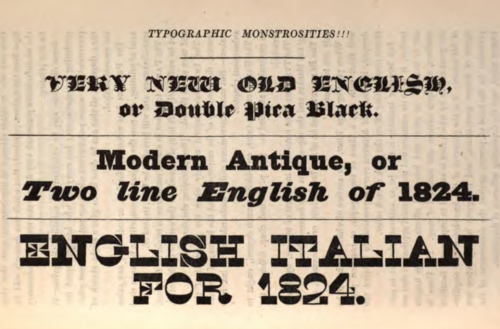
逆コントラストまたは逆ストレスの書体とは、ストレスが標準と逆になっている書体またはカスタムレタリングであり、つまり横線が最も太い。これは、縦線が横線と同じ幅か横線より太いというラテンアルファベットの書き方、特に印刷では普通のことであるが、その逆である。[5] [6] [7] [8] [9]その結果、文字が逆向きに印刷されているように見えるという劇的な効果が得られる。このスタイルは、19世紀初頭にディスプレイ書体の目を引く目新しいものとして発明された。このジャンルのデザインを作成した現代のフォントデザイナー、ピーター・ビラクは、これを「目立つ奇妙な書体を作成するための卑劣なトリック」と表現している。[10]
逆コントラスト文字は本文にはほとんど使われず、見出しやポスターなどの表示用途で使われることが多く、その珍しい構造は特に目を引くことがある。 [11] [12] 19世紀に特に一般的で、それ以降も時折復活している。太いセリフのためスラブセリフデザインとみなされ、そのジャンルの一部として特徴付けられることが多い。[7] [13]
逆コントラスト効果は、サンセリフ体などの他の種類の書体にも拡張されています。[7] [14]明るい文字が黒い背景に印刷される逆コントラスト印刷とは関係がありません。 [15]
歴史的背景
大文字はローマ字の角張った大文字、小文字は手書き文字をベースにした現代ラテン文字の発展を通じて、縦線は横線よりわずかに太いのが一般的だった。初期の「ローマン」または「アンティクア」書体はこのモデルに従い、文字の最も細い部分を斜めにし、下線を上線より太くして、右利きの筆者が羽ペンで書いたような書き方を模倣していた。(対照的に、ヘブライ文字はラテン文字の観点から見ると通常「逆コントラスト」で、縦線が薄くなっている。[16])
1475年頃にローマン体が登場してから18世紀後半にかけて、文字のデザインは比較的あまり発展しませんでした。当時のフォントのほとんどが本文用であり、デザインも比較的似通ったままで、イタリアの人文主義的な手書きの伝統に根ざしていたからです。[b]
17 世紀以降、活字鋳造工は現在では過渡期型、そして「モダン」またはディドン型と呼ばれる書体を開発しました。これらの書体は、以前よりもはるかに大きなストロークのコントラストを持ち、ストロークの幅の差も以前の書体よりもはるかに大きくなっていました。[d] [18] [19] [20]これらの書体は、当時の鋼鉄のようなカリグラフィに追いつくように、より構造化された文字形状を持ち、大胆に細い横線とセリフのディテールは、当時のますます高品質になる紙と印刷技術を誇示するものでした。[21] [22]さらに、これらの書体は厳密に垂直方向に強調されていました。例外なく、垂直線は水平線よりも太く、より幾何学的でモジュール化されたデザインを生み出しました。
この時期の2つ目の大きな発展は、印刷されたポスターの登場と、宣伝や広告のための看板や印刷物の使用の増加でした。これにより、目を引く新しいタイプの文字を開発したいという欲求が生まれました。[23]その結果、太字の「ファットフェイス」、古代に触発されたと思われるサンセリフ文字、そしてスラブセリフなどの新しいスタイルのレタリングと「ディスプレイタイプ」が登場し始めました。[24] [3] [25]これらの文字形態は、従来のセリフ文字の単なる拡大版ではなく、新しい出発点でした。[26] [27]おそらくより目を引くように、これらの新しいスタイルの文字は、非常に太字になることが多かったです。[2]
最初の逆コントラストタイプ
最も古い逆コントラストの書体は、1821年頃にさかのぼります。これはロンドンのキャスロン書体鋳造所(当時はキャスロン・アンド・キャザーウッドと呼ばれていました)によって作成されました。おそらく、当時の鮮明で高コントラストの「ディドン」書体とレタリングを模倣したものと思われます。[5] [10] [28] [29] [30]大文字のみのデザインで、鋳造所の鋼鉄製マスターパンチは、ロンドンのセントブライド図書館のコレクションに残っています。[5] [e]
Caslon Italian 書体は、デザイン上明らかに「概念的」であり、太字の特徴を意図的に取り入れ、一つずつ反転させている。Nick Sherman は、「太字は細字になり、細字は太字になるという、線の太さを反転させる非常に文字通りのアプローチを示している」とコメントしている。[12] [31]この書体はセリフが非常に太いため、文字を構成するセリフとメインのストロークの間の隙間が非常に小さく、これは「E」や「S」などの文字に見られる。この効果をさらに衝撃的なものにするために、三角形のセリフが反転され (文字に接するにつれて細くなり、太くなることはない)、「A」の太い線が通常の右側の位置 (右利きの書き手の手書きに一致する自然な位置) から左側に移動され、文字が逆向きに描かれたように見える。ポール・ショーはプリント誌に寄稿し、これを「19世紀で最も奇妙なスラブセリフ書体の一つ」と評した。[13] [f]ポール・バーンズとクリスチャン・シュワルツはこれを「ひねくれた[が]確信と自信を持って行われた」と評した。[5]
キャスロン社は、この書体を「イタリア風」と呼んだ。当時、いくつかのディスプレイ書体はエキゾチックな名前を付けられていた。同時期に、サンセリフ(後にスラブセリフ)書体に「エジプト風」、スラブセリフに「アンティーク」という名前が付けられた。これは、より奇抜なディスプレイ書体が作られるようになった世紀後半にますます一般的になった。[26] [33]シールズは、「キャスロンとキャサウッドの書体より前の例の証拠は見つかっていない」と書いている。[7] ニコレット・グレイは、それが「おそらく」イタリア起源であると信じるつもりだったが、印刷に関するフランスの著述家フランシス・ティボードーの影響を受けていた。ティボードーは、1921年の著書「印刷の手紙」で、このスタイルはフランス第一帝政(1804年 - 1814年/15年)の間にフランスで登場し、その後イギリスで初めて登場したと主張した。[34] [33]シールズ(2008)は、ティボードーの主張を否定している。「ティボードーは独りぼっちのようで、この書体の起源をフランスの鋳造所に帰していない。これまでの調査では、カスロン&キャサウッドのそれより古い例の証拠は見つかっていない。…日付が確認された最初のフランスの標本は、ローラン&デベルニーの1835年のブロードサイドだ」。[7]バーンズも「フランスやイタリアの文献を見たことがない」とコメントしているが[35]、デザインの起源は未解決のままである。[8] [9]逆コントラストのデザインは、上部と下部に強調された水平セリフを持つ古代ローマの大文字のルスティカ書体にわずかに似ているが、これは偶然かもしれない。[36]エジプシャンなどの他の名前も使用されていた。[37]
導入から数年のうちに、著名な印刷業者トーマス・カーソン・ハンサードは、これを「印刷上の怪物」と嘆いた。
流行と空想は、通常、一方の極端からもう一方の極端へと戯れる。[ディドン] 活字の鋭い細い線とセリフに 、逆 [スラブ セリフの] が成功した ... その特性は、文字を形成するストロークがすべて均一な太さであることだ! この後、さらに贅沢なことが考えられたと誰が考えただろうか? ただし、1 人の鋳造者の創意工夫により、すべてのセリフと細いストロークを太字に、太字を細字にすることで、自然な形状が逆転した書体が考案されたことは述べておく必要がある。おお! [過去の著名な鋳造者] モクソンとファン ダイク、バスカーヴィルとボドーニの神聖な色合い! 私たちの時代の流行が生み出した、ここで展示されている印刷の怪物について、あなた方は何と言っただろうか?そして、あなた方が私たちより先に生きてきたのと同じくらいの年月を経た次の世代の人々は、ここで標本として展示されている痕跡をどの時代やどの存在に帰属させるのでしょうか?[38]
対照的に、ウォルター・トレイシーは1986年にこのデザインを「従来の美的観点から判断されるべきではない、精神の遊び」と評した。 [39] [40]
1836 年に印刷された文書。Didone (本文)、「Italian」(「proceedings」という単語)、初期のサンセリフ フォントが使用されている。「Italian」の書体は Caslon のイタリア語版、またはその近似コピーである。この文書はミシガン州で印刷されたため、ロンドンで登場してから約 15 年でイタリア スタイルがどれだけ浸透していたかがわかる。
ウィリアム・レブンワースによる木版画の逆コントラスト、1830年代頃[41]
このデザインは成功したようで、米国やその他の地域に急速に広まった。[7]イタリアの書体は、1826年にスター・リトル社が米国で初めて発表した。[7]また、ニューヨークのジョージ・ブルース鋳造所は、1828年の見本帳にイタリアの書体を1つ掲載している。[1]同様のデザインの多くのバージョンが、金属活字と木製活字の両方で発表された。[42] [g]このコンセプトの拡張には、紛らわしいことに「イタリアン・イタリック」と呼ばれるイタリック体、バックスラント、サンセリフ体のバージョンが含まれていた。[7]
同じ頃、ポスター印刷では木活字が人気を集めていた。以前は、繰り返しの形状に簡単に鋳造できる金属が一般的だったが、 1827年にダリウス・ウェルズが横型ルーターを、1834年にウィリアム・レブンワースがパンタグラフを導入したことで、木活字の大量生産が可能になった。木活字は金属活字よりもはるかに軽く、安価だった。[46] 1837年以降、いくつかのイタリアのデザインが木活字として発売された。[7]
イタリア風のデジタル化はいくつかなされている。ピーター・ビラクの Karloff は、大文字と小文字の通常および対応する逆コントラストのフォントのファミリーで、低コントラストのスラブセリフのデザインが付いており、すべて同じ基本構造になっている。ビラクと彼の同僚は、従来の Didone フォントのコントラストを厳密に反転し、その 2 つを低コントラストのスラブセリフに補間しようとした。これらは、ボリス・カーロフにちなんで Karloff Positive、Negative、Neutral としてリリースされている。[10] [30] [47] [48]非常にコントラストの高い大文字のみの復活は、クリス・ソワーズビーの Maelstrom で、これもサンセリフのデザインがある。[49] [50] [31]コマーシャル・タイプのポール・バーンズは、イタリアのリバイバル版をリリースした。このプロジェクトのために行われた研究に関する詳細な情報と、それに付随するフランスのアンティークデザイン(下記参照)もリリースした。 [51] [8] [9]ビレッジ・タイプのアーバーも小文字で、マッチ&ケロシンのスラブ・シェリフは大文字のみで、"A"の右側に慣例的な強勢がある。[52] [53]ジャスティン・ハウズが個人使用のために別のデジタル化を行った。[40]
フレンチクラレンドン
逆コントラストのアイデアは、クラレンドンとして知られる別のジャンルのスラブセリフ書体と融合しました。19世紀中期から後半にかけて、特に米国で人気のスラブセリフ書体ジャンルであるクラレンドンの逆コントラストのバリエーションを活字鋳造所が提供し、文字の上部と下部に大きなブロックセリフを作成することが一般的になりました。これは「フレンチクラレンドン」書体として知られていました。[54] [55]フレンチクラレンドン書体の利点は、文字を細くしたまま非常に大きく目を引くセリフを可能にすることで、凝縮された非常に太い書体を求めるポスターメーカーの要望に合っていました。[56]フレンチクラレンドンのデザインは、ポスターの大きな文字に使用される木製活字で作成されることがよくあります。これらは「ワイルドウェスト」印刷に関連付けられることが多く、サーカスのポスターや西部劇の募集広告で見られますが、このスタイルは実際にはこの時期に世界中の多くの地域で使用されていました。このスタイルは「サーカス文字」と呼ばれることもある。[11] [54]この方法は、より職人的な印刷業者の間ではあまり人気がなかった。デヴィンは1902年に「嫌われるには、見られるだけで十分だ」とコメントした。 [57]ヨーロッパでは、このスタイルはキャスロンの名にちなんでイタリア文字と呼ばれることもあった。文字の中央の横線(Hの横棒など)が太いことが多いが常に太いわけではないオリジナルのキャスロン書体とは対照的に、フランスのクラレンドン書体は、太い線は上と下のみで、内側の横線はすべて細く、一般的に「概念的に」逆コントラストが少なく、セリフは上と下の太い線以外はより慣習的な配置になっている。[36]